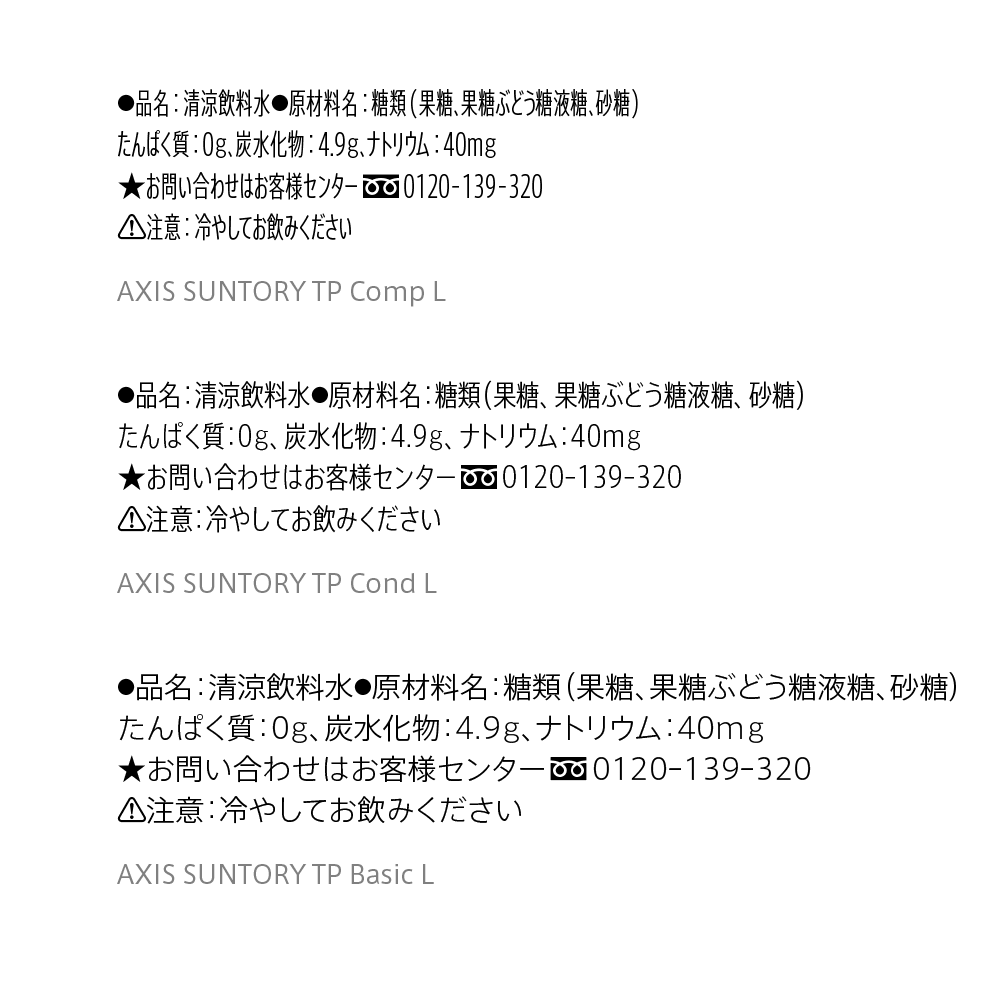
TPフォント使用事例紹介「伊右衛門 ジャスミン」
パッケージや書籍、webサイト、広告など各媒体でのTPフォントの使われ方を事例を元に紹介していきます。今回は、飲料水の伊右衛門シリーズ「ジャスミン」です。
使用TPフォント:AXIS Font、TPスカイラウンド50、AXIS SUNTORY TP
「現代的なすっきりとした文字で爽やかな香りを表現」
伊右衛門 ジャスミンは、華やかな香りと緑茶由来の心地よい渋み・キレが感じられる、 緑茶仕立てのジャスミン茶です。 パッケージの和文部分には、現代的なすっきりとした文字が、 軽やかな印象のデザインに効果的に使用されています。
使用されているタイププロジェクトのフォント:AXIS Font
商品名の「ジャスミン」や「香り、爽快」は、現代的ですっきりとした印象があるAXIS Fontです。ジャスミンの爽やかな香りをAXIS Fontが効果的に感じさせてくれます。
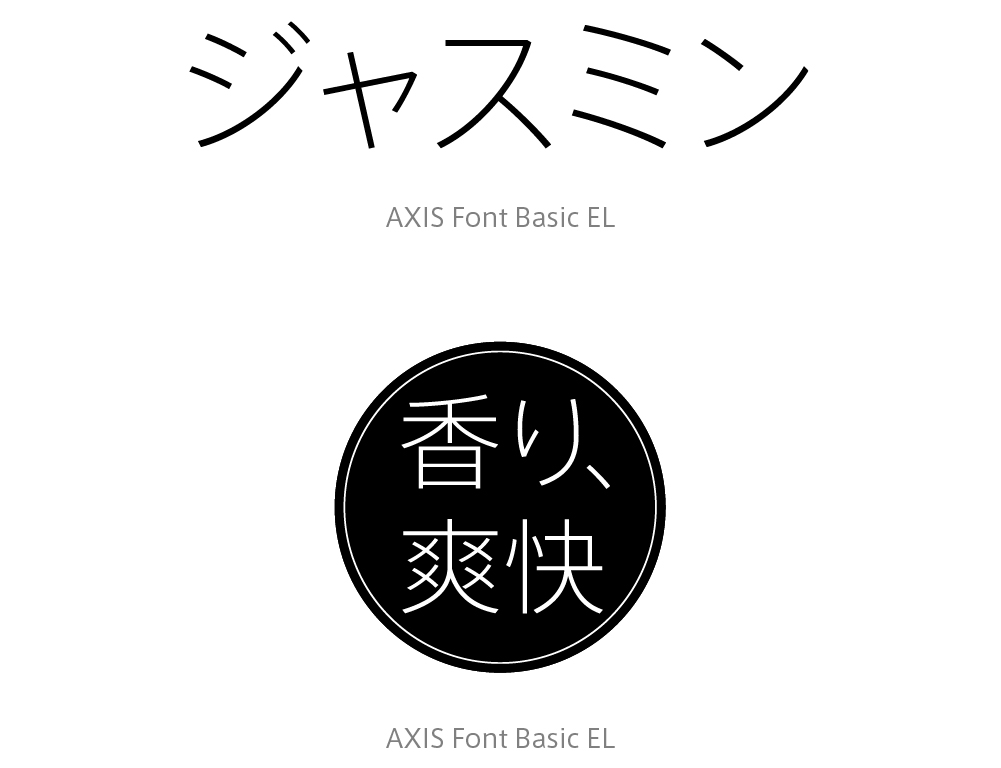
使用されているタイププロジェクトのフォント:TPスカイラウンド50
ホットでは、「ジャスミン」や「あったかい」の部分は、抑揚のあるサンセリフ体TP Skyの角をわずかに丸めたTPスカイラウンド50です。
ジャスミンの爽やかな香りはそのままに、あたたかいマイルドな印象を感じさせてくれます。
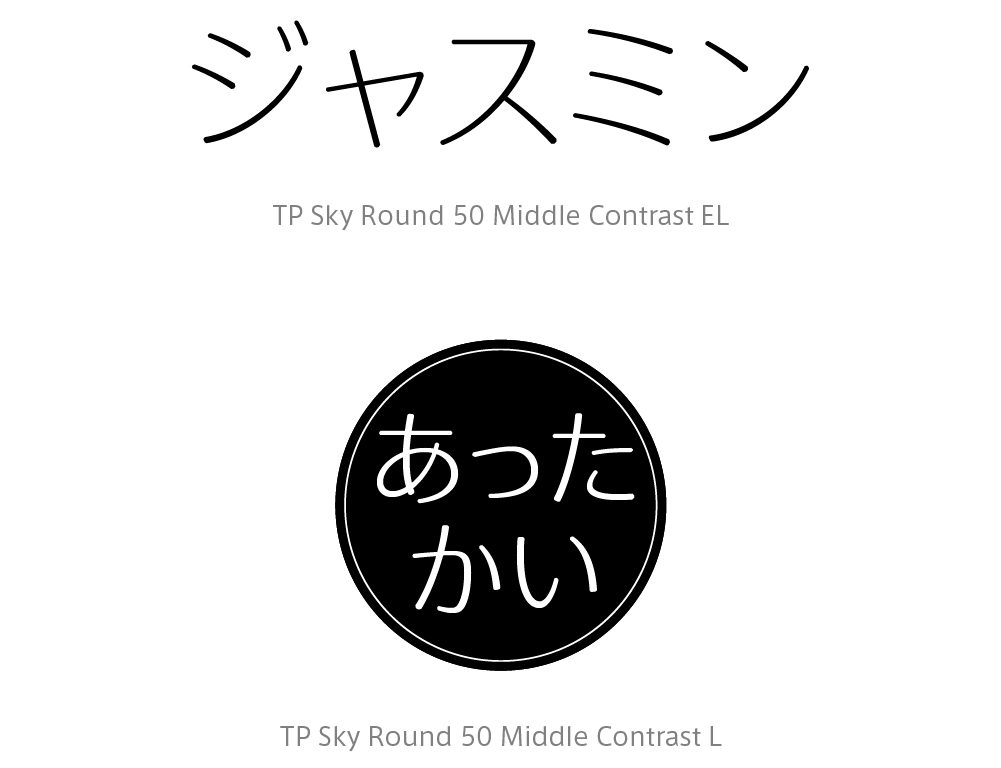
使用されているタイププロジェクトのフォント:AXIS SUNTORY TP
アイス、ホット共に、原材料や注意表記などの部分は、AXIS SUNTORY TPです。
狭いスペースに多くの情報を記載する必要があり、なおかつ可読性を維持することが求められる部分です。